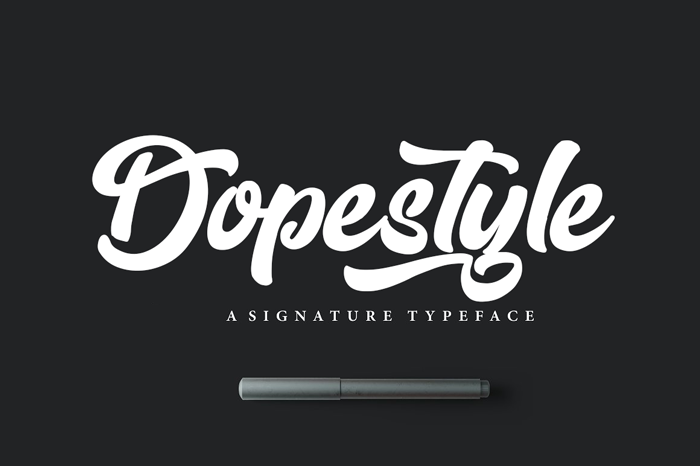
A Dopestyle Script Font é uma assinatura tipográfica criada para atender uma ampla gama de necessidades designísticas. Perfeita para criações de logotipo, posters, ilustrações digitais e até mesmo sinalização em ambientes comerciais limpos e sofisticados, ela se destaca como um recurso valioso para designers que valorizam a estética cuidada e os detalhes artísticos. Seu design elaborado e sua versão completa com licença comercial são oferecidos pela Octotype, onde também você pode encontrar outros recursos tipográficos de alta qualidade. A Dopestyle é mais do que uma fonte; ela é um legítimo complemento para qualquer projeto que busque expressar criatividade através da palavra. Em seu design cuidadosamente construído pelo designer Hamilton, a Dopestyle captura nuances sutis e elegância em cada letra, tornando-a ideal para quem procura personalizar seu trabalho de design com um toque único. Seja você um profissional experiente ou alguém que está começando sua jornada na criação visual, a Dopestyle é uma fonte certa para incluir na sua biblioteca de recursos. Com um olhar atento aos detalhes e uma paixão por criatividade e sofisticação, essa fonte traz à vida suas ideias designísticas com estilo único.